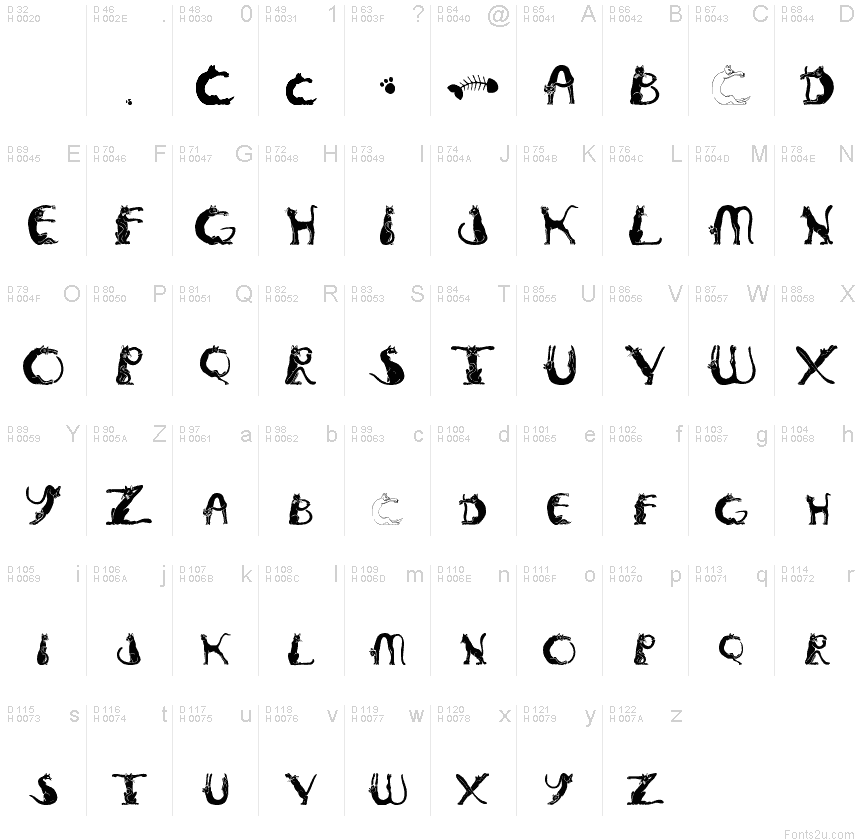
Pussyfoot, un font gratuito in stile cartoon creato da WEB DOG, trasforma le lettere in sagome feline che si stiracchiano, si riposano e si raggomitolano. L'idea è semplice e memorabile: ogni carattere prende forma attraverso un dorso arcuato, una coda curva o una posa felina, rendendo il font giocoso senza mai perdere la chiarezza delle lettere.
Funziona al meglio dove il motivo felino è il protagonista: branding per negozi di animali, volantini veterinari, copertine di libri per bambini, poster di eventi e brevi titoli in stile logo. Essendo un font gratuito, Pussyfoot è particolarmente utile per titoli, monogrammi o capolettera che richiedono un tocco vivace e disegnato a mano, lontano dai soliti stili generici.
Pussyfoot